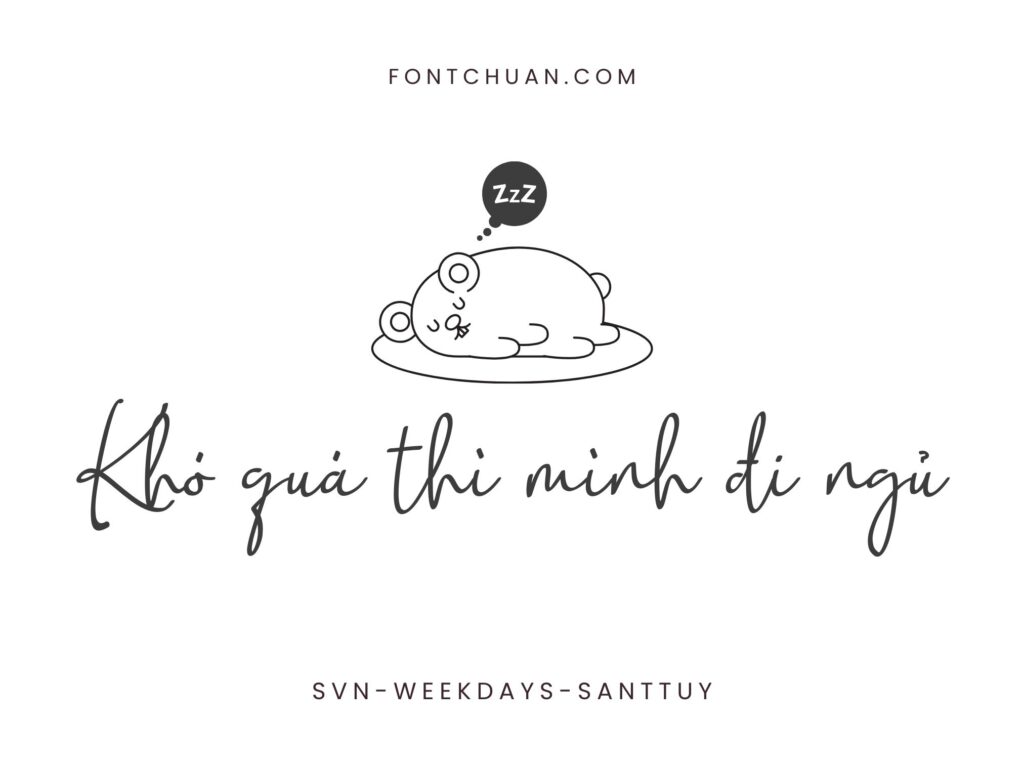
Font SVN Weekdays Santtuy Việt Hóa
Tác giả Font: Alde Saputro
Font SVN Weekdays Santtuy là phiên bản Việt hóa của kiểu chữ Weekdays Santtuy, được thực hiện bởi Styleno.1 Fonts. Weekdays Santtuy là một kiểu chữ viết tay thanh lịch và tự nhiên, được thiết kế bởi Alde Saputro và phát hành bởi Aldedesign. Font này nổi bật với các đường nét mềm mại, tạo cảm giác thân thiện và gần gũi. Weekdays Santtuy bao gồm các chữ cái in hoa, in thường, chữ số và các ký tự đặc biệt, hỗ trợ đa ngôn ngữ, phù hợp cho nhiều mục đích sử dụng khác nhau như thiết kế logo, thiệp mời, tiêu đề và các ấn phẩm truyền thông.
SVN Weekdays Santtuy lý tưởng cho các dự án thiết kế yêu cầu sự cá nhân hóa và tinh tế, như thiệp mời, logo, tiêu đề và các ấn phẩm truyền thông. Các ngành nghề như thiệp cưới, ẩm thực và spa có thể tận dụng font này để tạo điểm nhấn trong thiết kế. Ngoài ra, font cũng thích hợp cho các sự kiện như Tết, Valentine, Sinh nhật và các lễ hội khác.